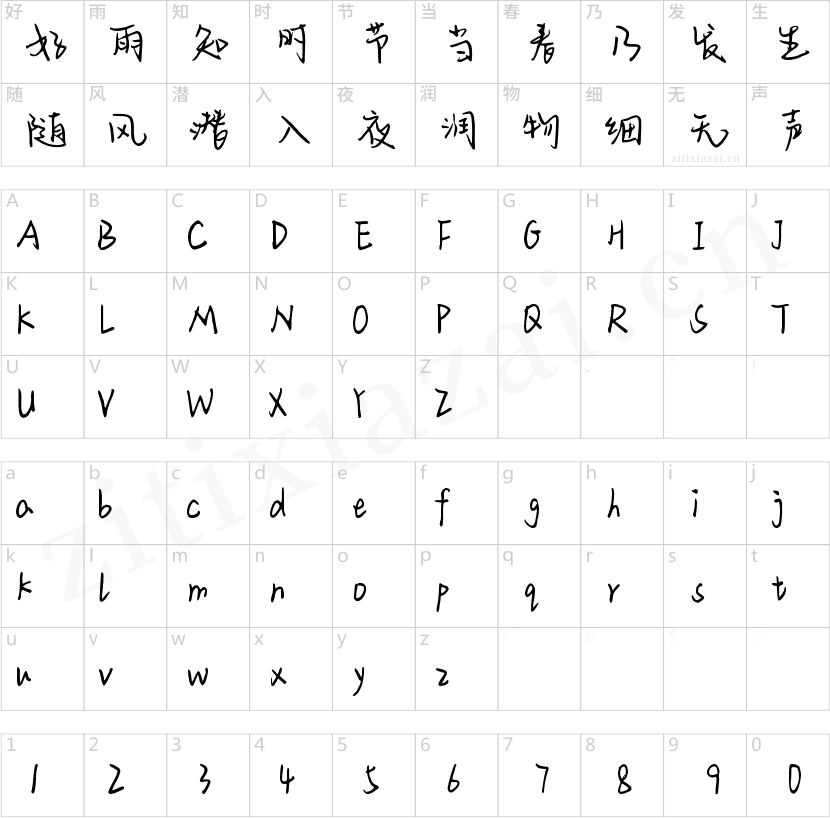
Aa追风少年的天空
Aa追风少年的天空字体
Aa追风少年的天空是一款非常具有艺术性的字体,它的设计灵感来源于对古典艺术的研究,同时又融入了现代字体设计的元素。字形优美,笔画粗细变化自然,给人以大气、典雅的感觉。Aa追风少年的天空是一款既传统又现代的字体,它的设计充满艺术感,美观大方,实用性也非常强。无论是对于设计师还是对于普通读者来说,都是一种非常不错的字体选择。Aa追风少年的天空适合用于具有艺术感的场合,比如海报、宣传单张、书籍封面等。由于其字形流畅且具有动态感,也适合用于大量的文本排版,如报纸、杂志等。